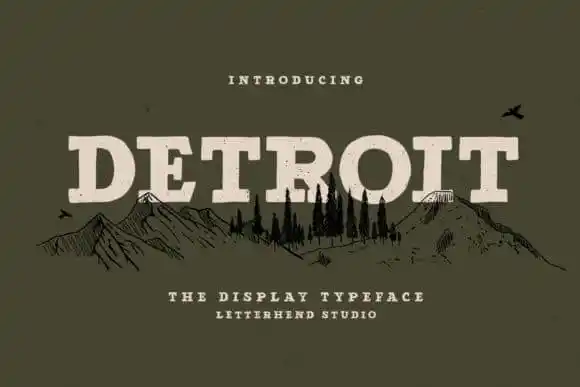
Detroit Display Font é uma elegante fonte de estilo serifa estreito inspirada nos posters vintage dos anos 80. Ela exibe um tom audacioso e sofisticado, perfeitamente adaptável para uso em logotipos, identidade visual, embalagens e design gráfico de diversas formas. Seus caracteres grossos e redondos oferecem uma textura única que brilha sob diversos ambientes tipográficos. Esta fonte masterminda pelo designer letterhend é uma verdadeira escolha essencial para quem busca um estilo único e impressionante. Ela combina a elegância dos anos 80 com a modernidade contemporânea, fazendo dela uma ótima opção para designers que procuram agregar um toque vintage em seus projetos. Detroit Display Font é o tipo perfeito para aqueles buscando uma fonte que brilhe de forma sofisticada e vibrante.